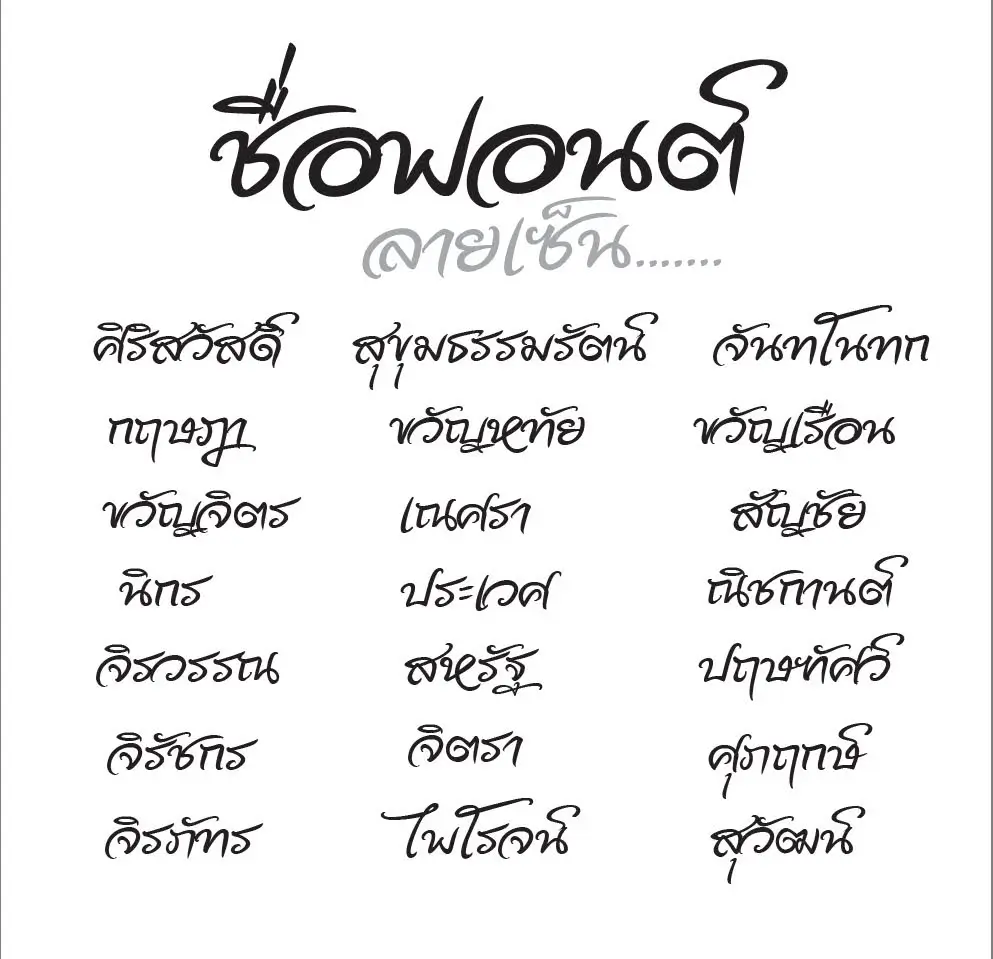
ฟอนต์ เคอาร์ต-ลายเซ็น (Kart-Rai Zen) – เป็นฟอนต์ที่เขียนเน้นใช้งานแนว #ฟอนต์ลายมือ #ฟอนต์ลายเซ็น #ฟอนต์เขียนมือ เป็นฟอนต์ตัวอย่าง สามารถใช้ครอบคลุมหลายโปรแกรมครับ
เคอาร์ต-ลายเซ็น (Kart-Rai Zen)